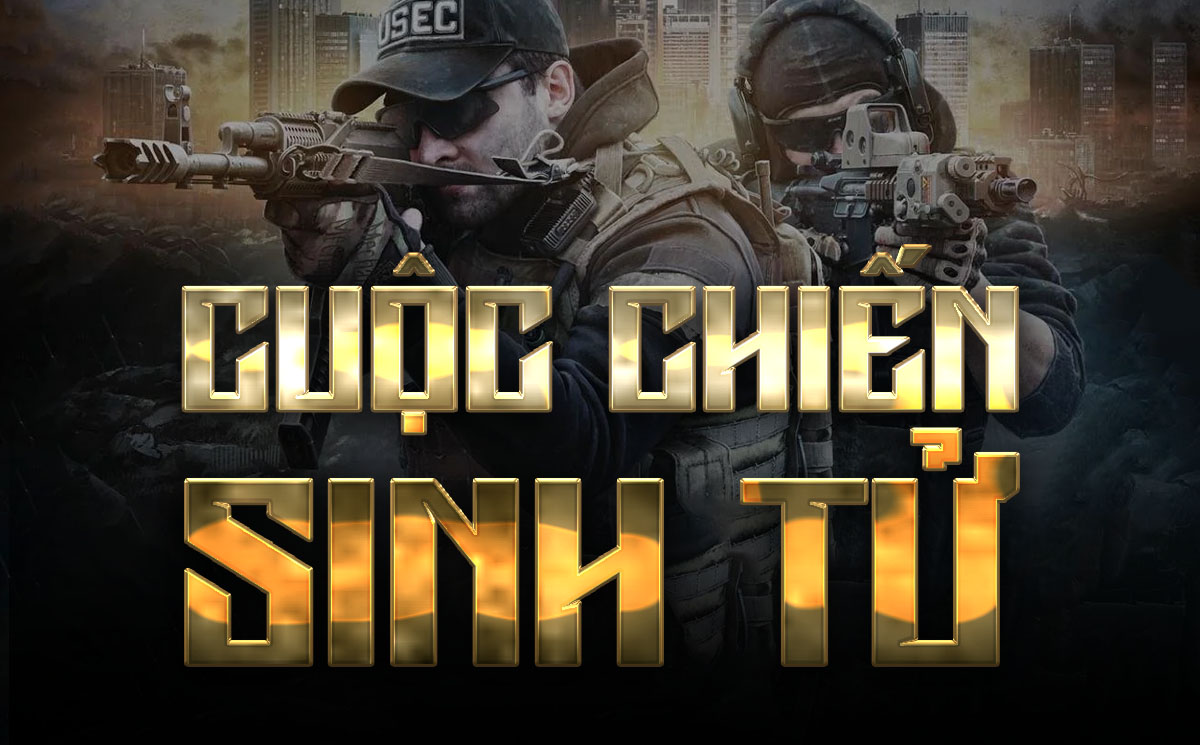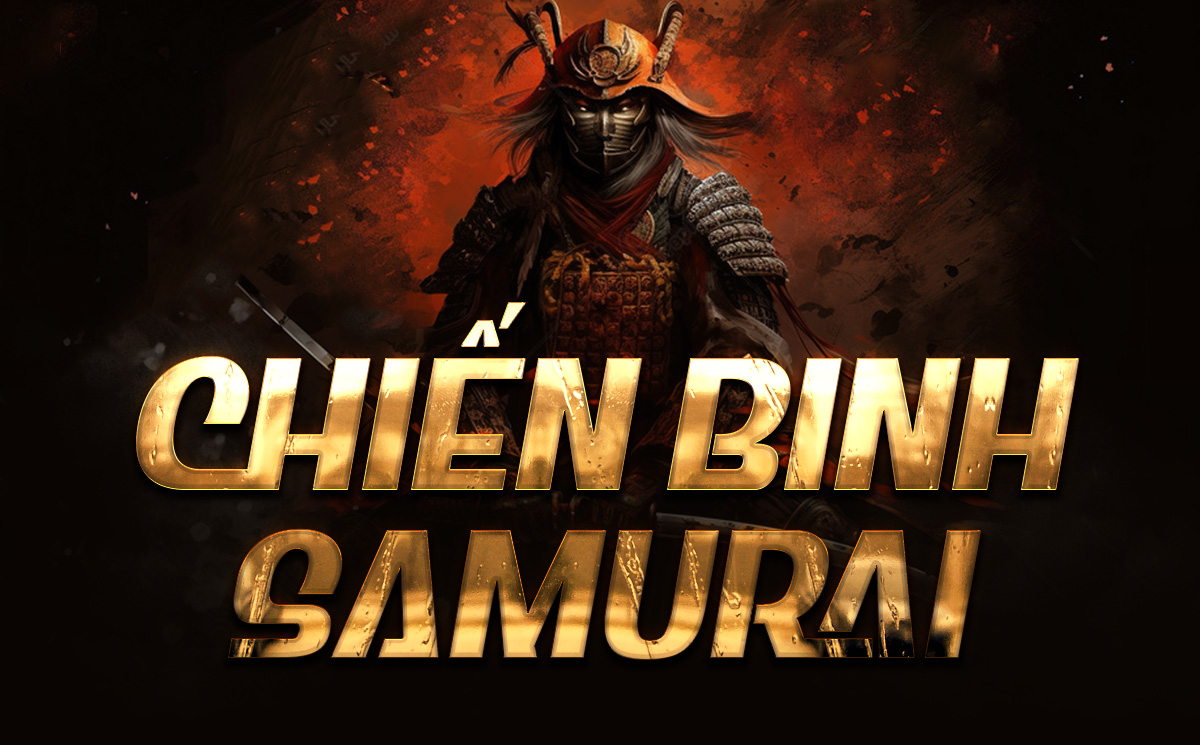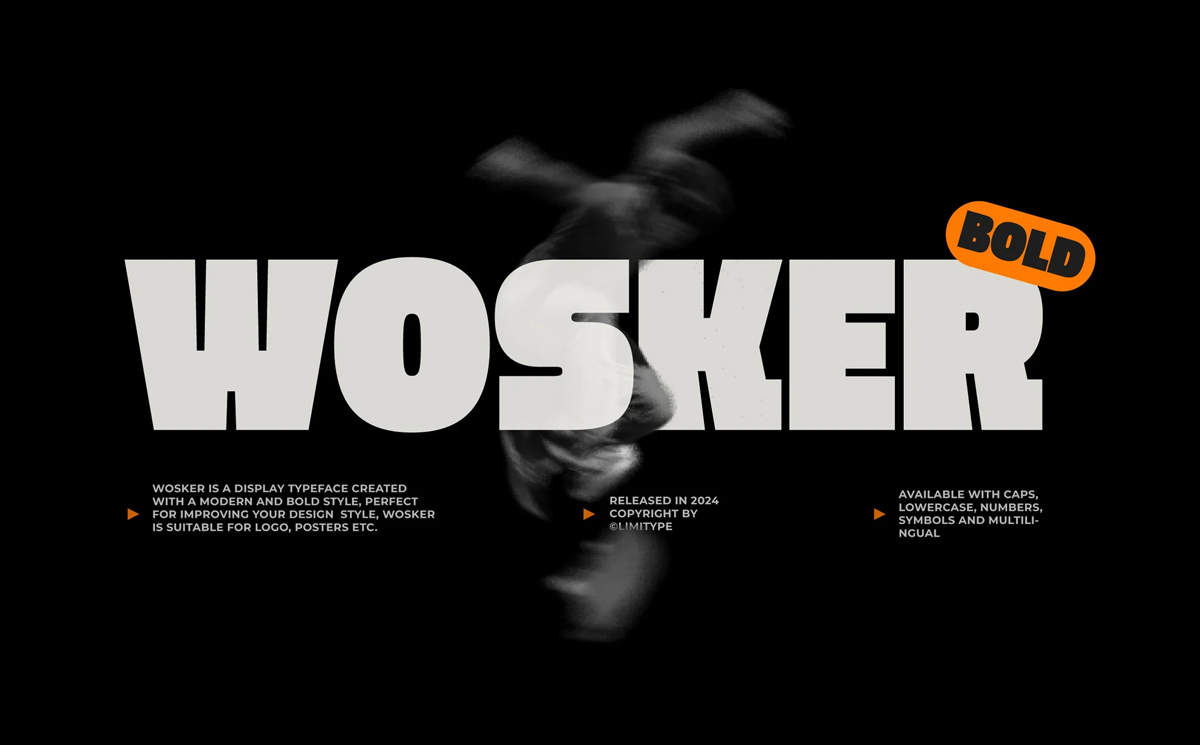
Top 18 font chữ cho local brand thời trang, lookbook và campaign social
Gợi ý font TH Việt hóa cho local brand thời trang, lookbook và campaign social.
Local brand thời trang cần font có cá tính rõ, đủ nổi trên poster drop sản phẩm, lookbook, story, reels và vẫn đọc tốt tiếng Việt.
Bài viết này gợi ý 18 font TH Việt hóa phù hợp cho streetwear, sportswear, basic wear cá tính, phụ kiện, lookbook theo mùa và campaign social. Mỗi font đều có link tải và ảnh preview để bạn kiểm tra nhanh.
Cách chọn font cho local brand thời trang
Trước khi tải font, hãy xác định vai trò của chữ: font logo, font headline campaign, font lookbook và font phụ cho caption, size chart hoặc thông tin mua hàng.
Với lookbook, font nên tôn ảnh sản phẩm. Với streetwear, các font cứng, nghiêng, sport hoặc brush sẽ tạo năng lượng mạnh hơn. Với social, hãy test ở khung vuông, story dọc và thumbnail video.
Top 18 font TH Việt hóa cho local brand thời trang, lookbook và campaign social
Dưới đây là các font phù hợp cho nhiều sắc thái local brand khác nhau: từ streetwear gai góc, sportswear năng động, techwear hiện đại đến lookbook tối giản. Bạn có thể tải từng font, test với tên thương hiệu thật, rồi chọn 2-3 font để tạo hệ chữ dùng lâu dài.
1. TH Dark Sincity
TH Dark Sincity phù hợp với cá tính cho key visual streetwear. Bạn có thể dùng font này cho headline bộ sưu tập, poster drop áo, cover reel, thumbnail lookbook và chữ lớn trên banner sale giới hạn. Khi triển khai, hãy giữ số chữ ngắn, nền tương phản mạnh và không dùng cho đoạn mô tả dài và phối thêm font phụ rõ ràng cho giá, size, ngày mở bán hoặc mô tả sản phẩm.
2. TH Geardive
TH Geardive phù hợp với tương lai, thể thao và năng lượng. Bạn có thể dùng font này cho campaign áo khoác, sneaker, activewear, poster collab hoặc social post cần cảm giác tốc độ. Khi triển khai, hãy phối với font phụ gọn để thông tin size, giá và ngày mở bán đọc rõ trên mobile và phối thêm font phụ rõ ràng cho giá, size, ngày mở bán hoặc mô tả sản phẩm.
3. TH KAIRO
TH KAIRO phù hợp với hiện đại pha retro cho local brand có cá tính riêng. Bạn có thể dùng font này cho lookbook theo mùa, poster capsule collection, ảnh bìa campaign và các layout có cảm giác nostalgic. Khi triển khai, hãy giữ bảng màu tiết chế để chất retro không làm tổng thể bị cũ hoặc nặng và phối thêm font phụ rõ ràng cho giá, size, ngày mở bán hoặc mô tả sản phẩm.
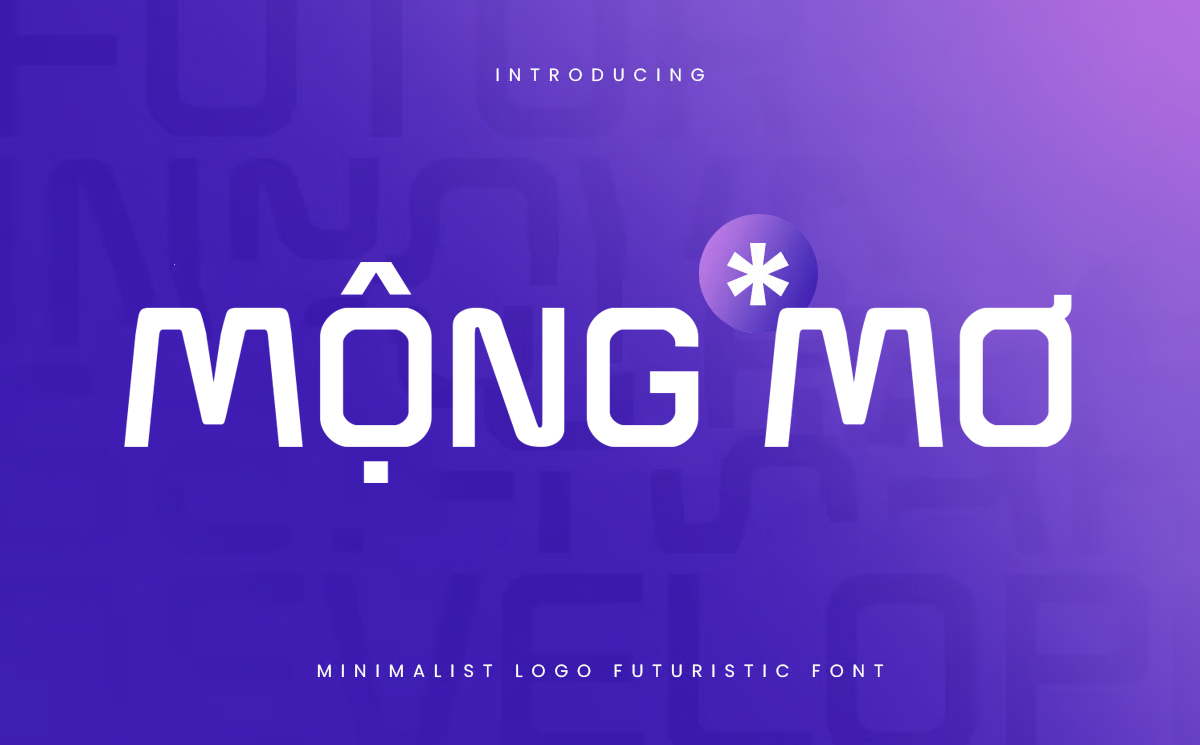
4. TH Infinity
TH Infinity phù hợp với display cứng cáp cho local brand mạnh. Bạn có thể dùng font này cho logo chữ, slogan ngắn, typography trên áo, poster drop limited và ảnh bìa Facebook. Khi triển khai, hãy hợp bảng màu đen, trắng, đỏ, bạc hoặc neon, nhưng nên tránh dùng quá nhiều hiệu ứng viền và phối thêm font phụ rõ ràng cho giá, size, ngày mở bán hoặc mô tả sản phẩm.
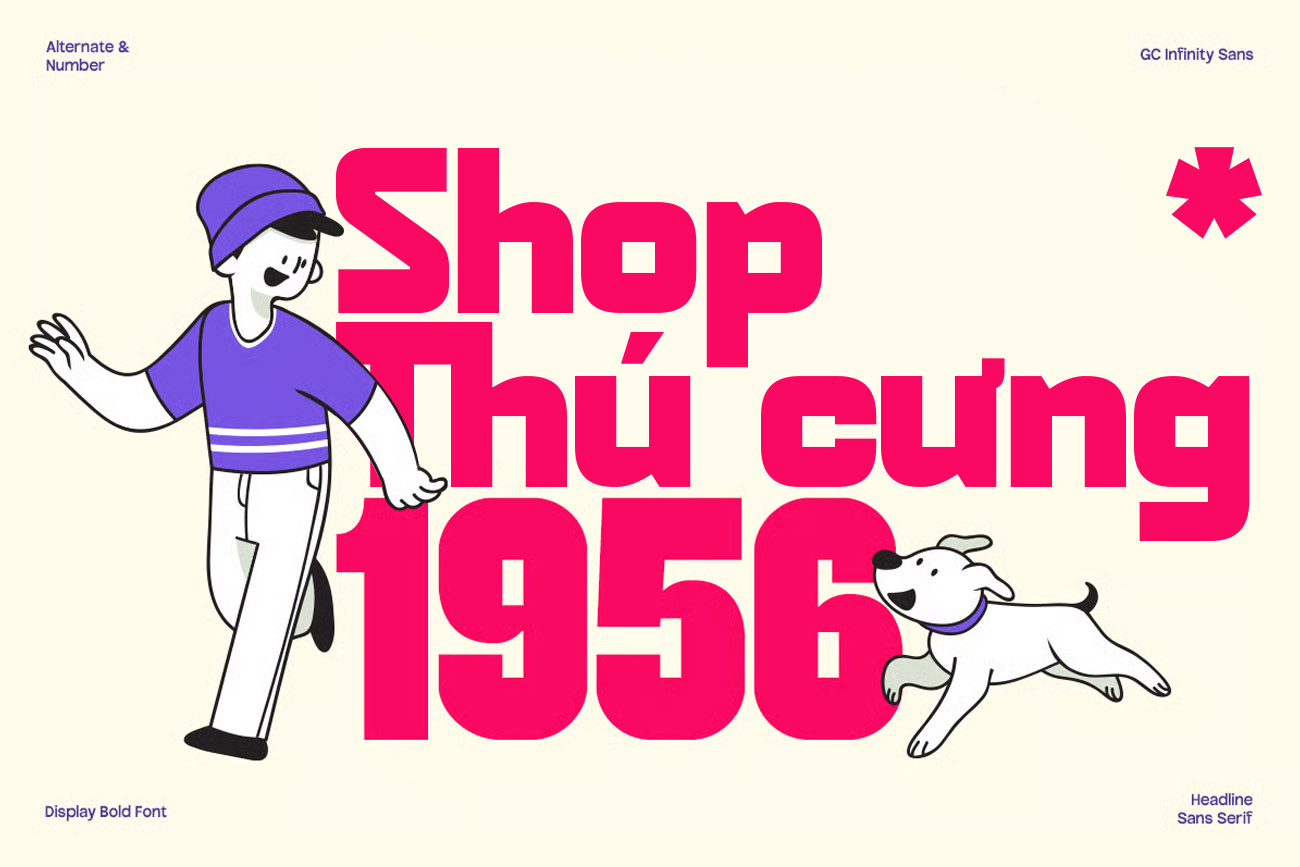
5. TH Bringas
TH Bringas phù hợp với mạnh mẽ cho sportswear và streetwear. Bạn có thể dùng font này cho áo bóng rổ, áo oversize, campaign thể thao đường phố, badge thương hiệu và poster sự kiện. Khi triển khai, hãy nên đặt ở kích thước lớn để các góc cạnh có đủ không gian thở và phối thêm font phụ rõ ràng cho giá, size, ngày mở bán hoặc mô tả sản phẩm.
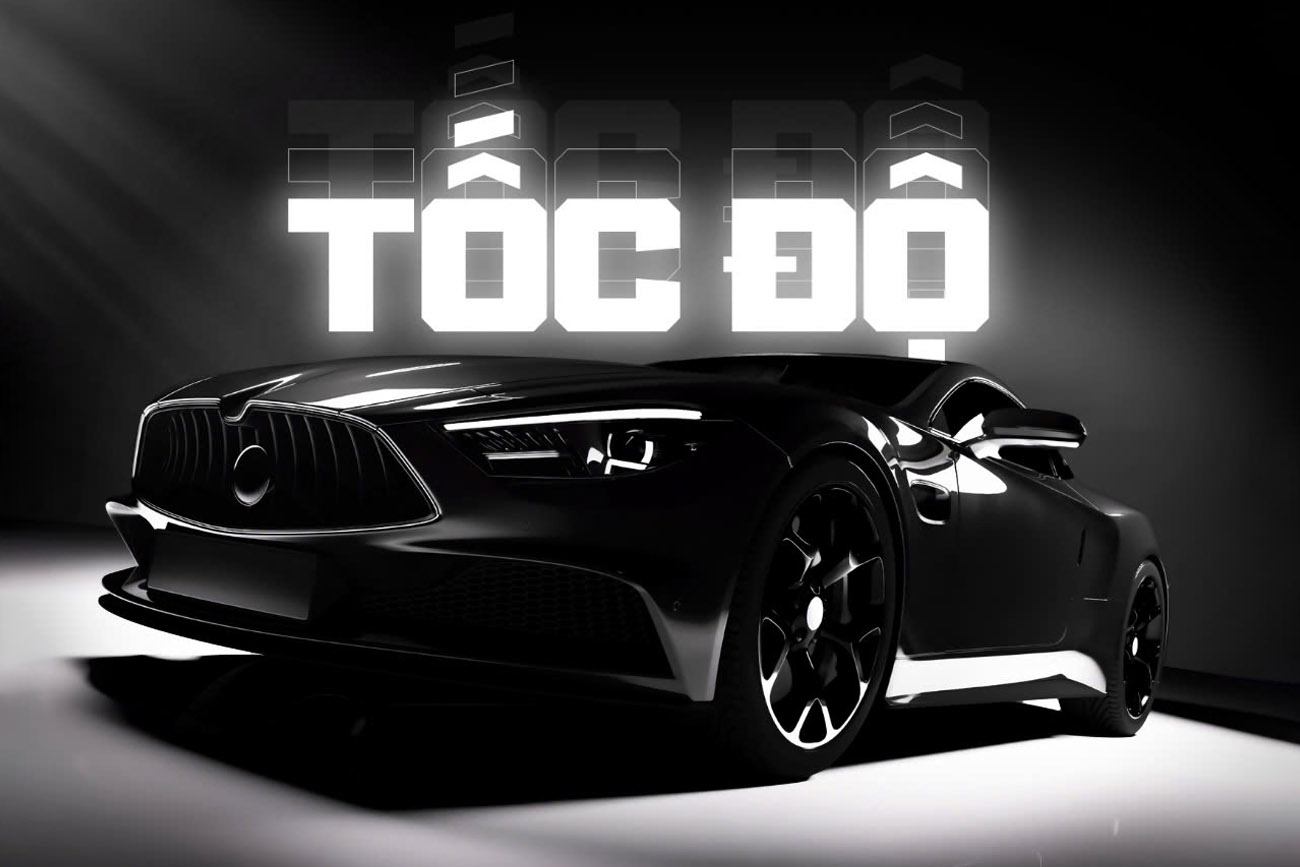
6. TH Giabe
TH Giabe phù hợp với sans display hiện đại và dễ làm brand kit. Bạn có thể dùng font này cho logo local brand trẻ, lookbook tối giản, tiêu đề website, social template và landing page bộ sưu tập. Khi triển khai, hãy dùng tốt khi thương hiệu muốn cá tính nhưng vẫn sạch, không quá hầm hố và phối thêm font phụ rõ ràng cho giá, size, ngày mở bán hoặc mô tả sản phẩm.
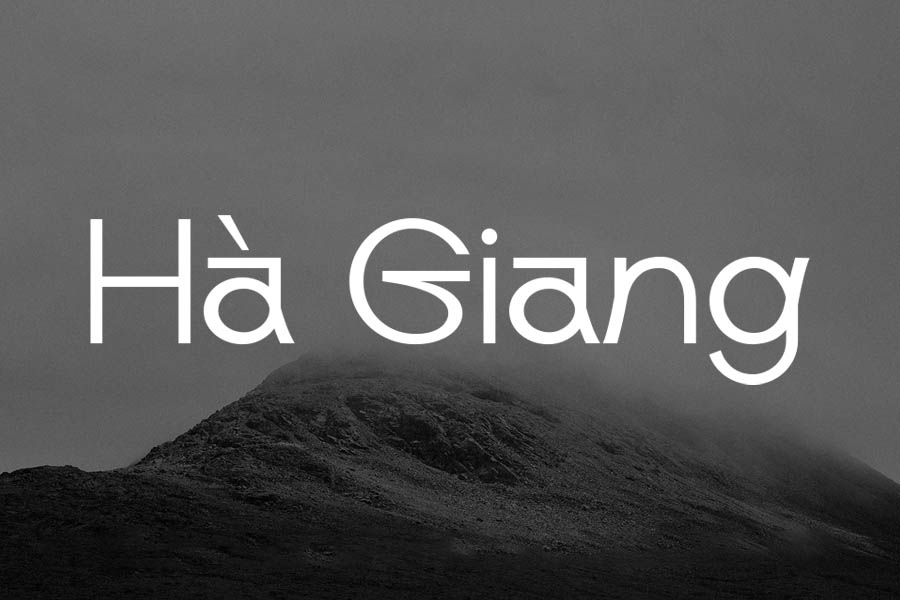
7. TH Rakend
TH Rakend phù hợp với bứt phá, dày và có lực. Bạn có thể dùng font này cho drop áo graphic, poster sale cuối mùa, slogan ngắn trên packaging và bộ sticker thương hiệu. Khi triển khai, hãy không nên dùng ở cỡ chữ nhỏ vì nét mạnh cần khoảng trống để nhìn rõ và phối thêm font phụ rõ ràng cho giá, size, ngày mở bán hoặc mô tả sản phẩm.
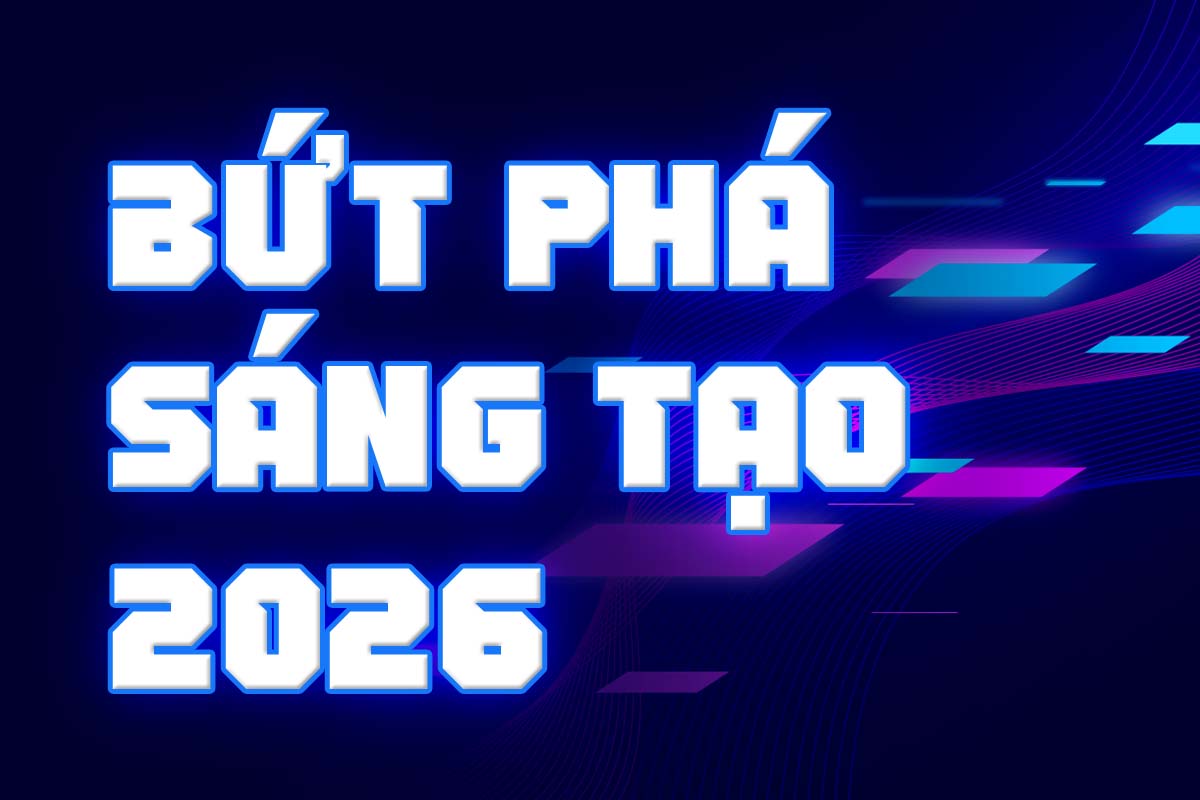
8. TH Myahewa Regular
TH Myahewa Regular phù hợp với tốc độ cho campaign năng động. Bạn có thể dùng font này cho poster chạy bộ, áo team, bộ sưu tập performance, motion graphic và thông báo mở bán nhanh. Khi triển khai, hãy đặt cùng ảnh chuyển động, motion blur hoặc bố cục chéo sẽ phát huy tinh thần tốc độ và phối thêm font phụ rõ ràng cho giá, size, ngày mở bán hoặc mô tả sản phẩm.
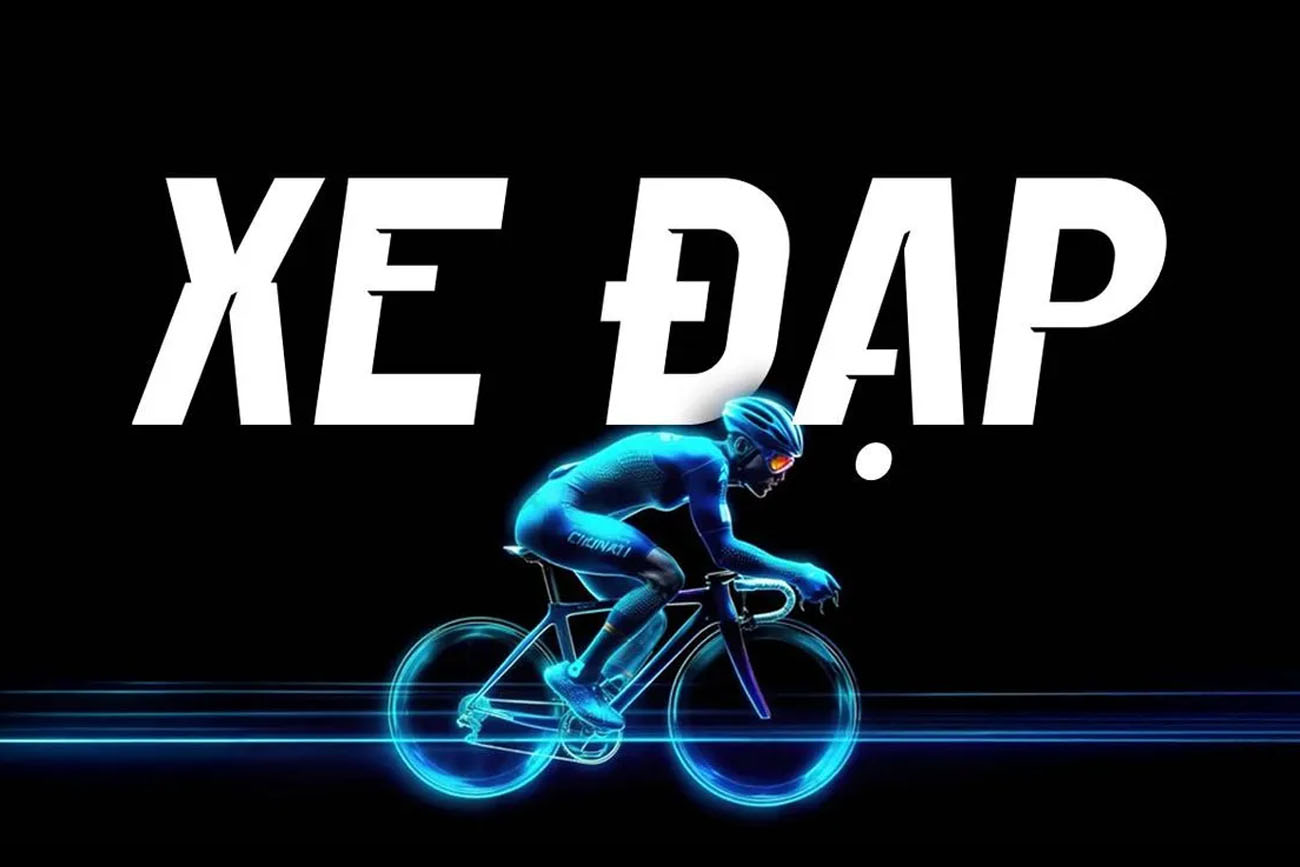
9. TH Glister
TH Glister phù hợp với không chân cứng, rõ và chắc. Bạn có thể dùng font này cho poster minimal, logo phụ, bảng size, caption ngắn trên ảnh sản phẩm và tiêu đề landing page. Khi triển khai, hãy phù hợp khi local brand muốn hình ảnh chắc chắn nhưng không quá thể thao và phối thêm font phụ rõ ràng cho giá, size, ngày mở bán hoặc mô tả sản phẩm.
Bạn có thể bắt đầu với TH Dark Sincity, TH Geardive, TH KAIRO, TH Infinity, TH Giabe, TH Galvitra, TH Teknaf hoặc TH Wosker, sau đó test với tên collection thật, ảnh sản phẩm thật và khung social thật. Khi font, màu sắc, ảnh và bố cục đi cùng một hướng, local brand sẽ có diện mạo nhất quán và dễ được ghi nhớ hơn.